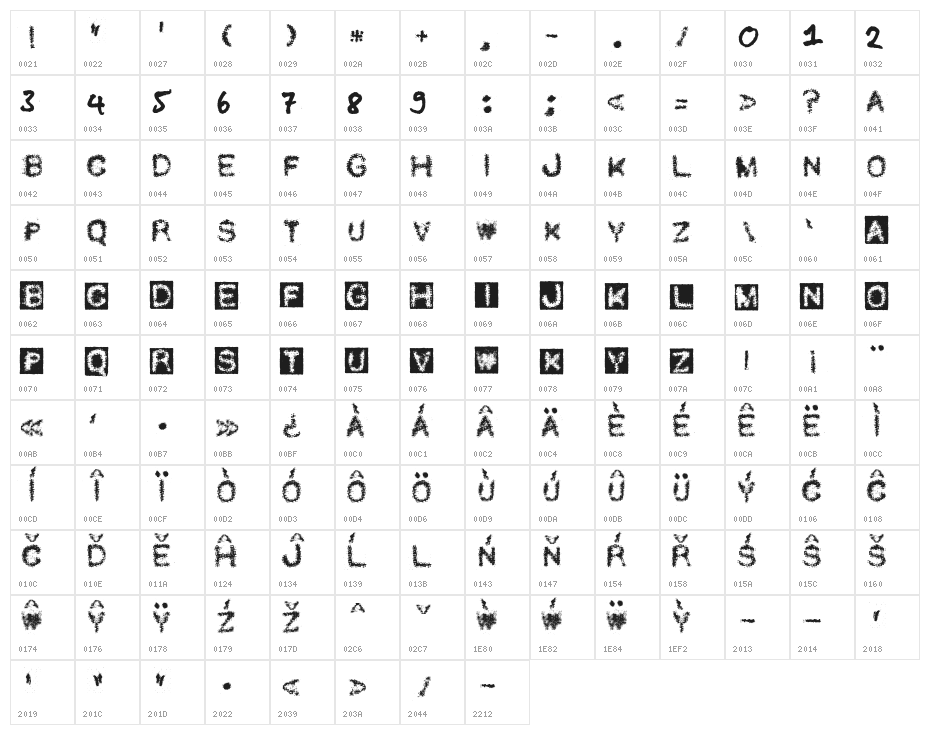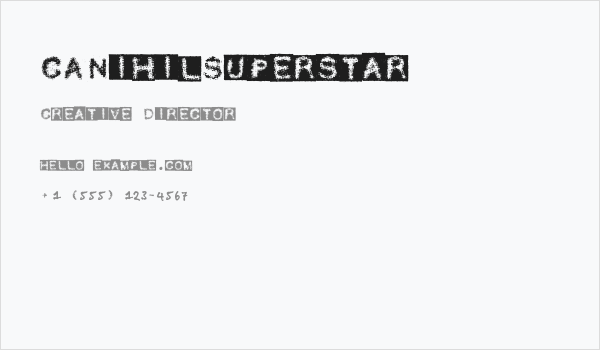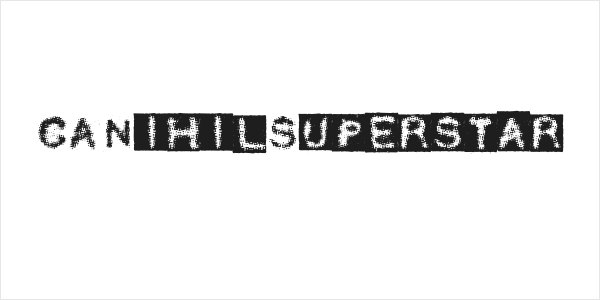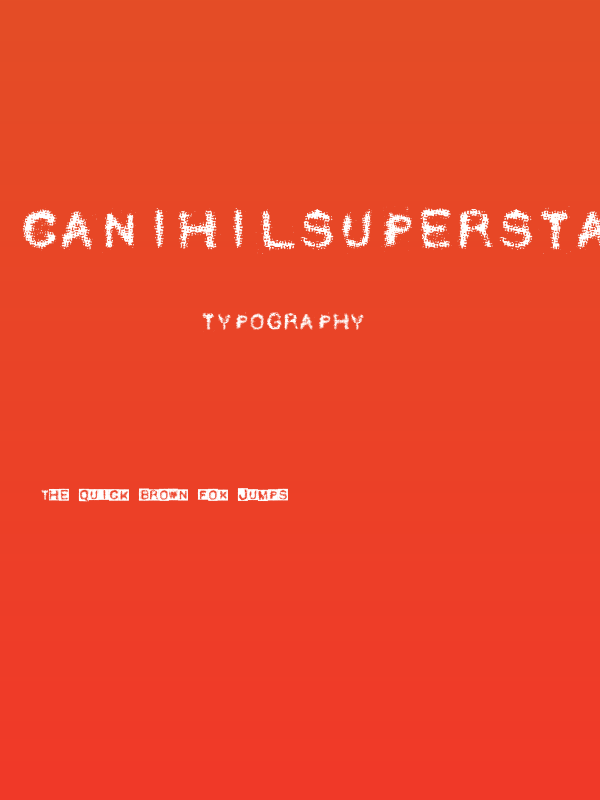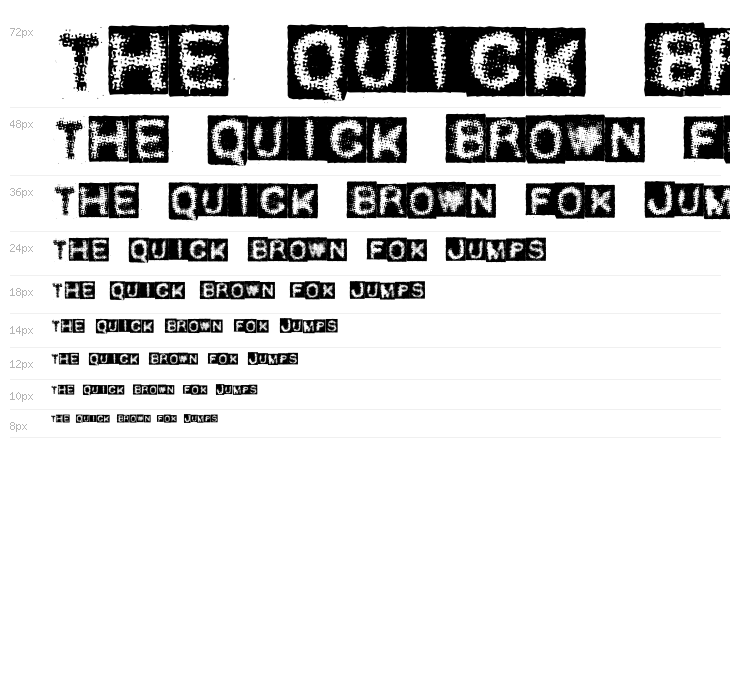
CANihilSuperstar Font
| Stil general | Vintage, Grunge |
| Proiecte propuse | Ideal for album covers, posters, branding for edgy or alternative products, and any design needing a bold, vintage touch. |